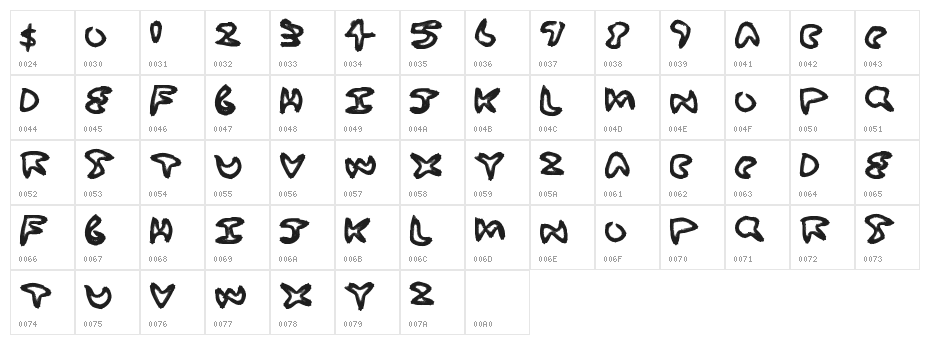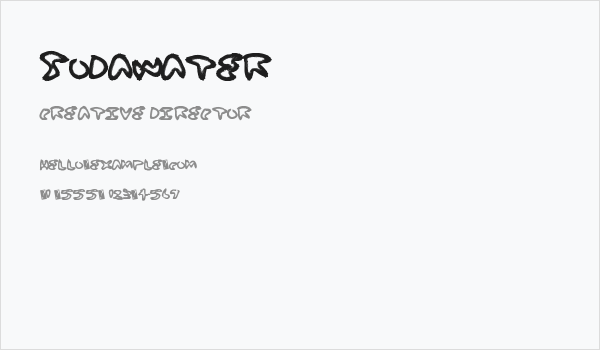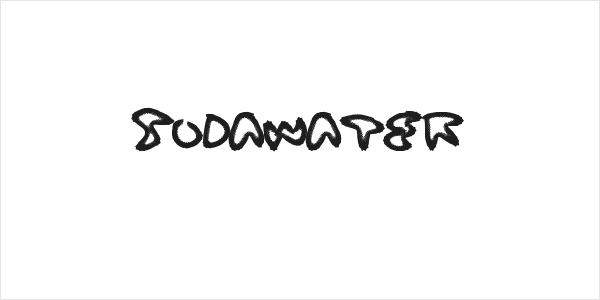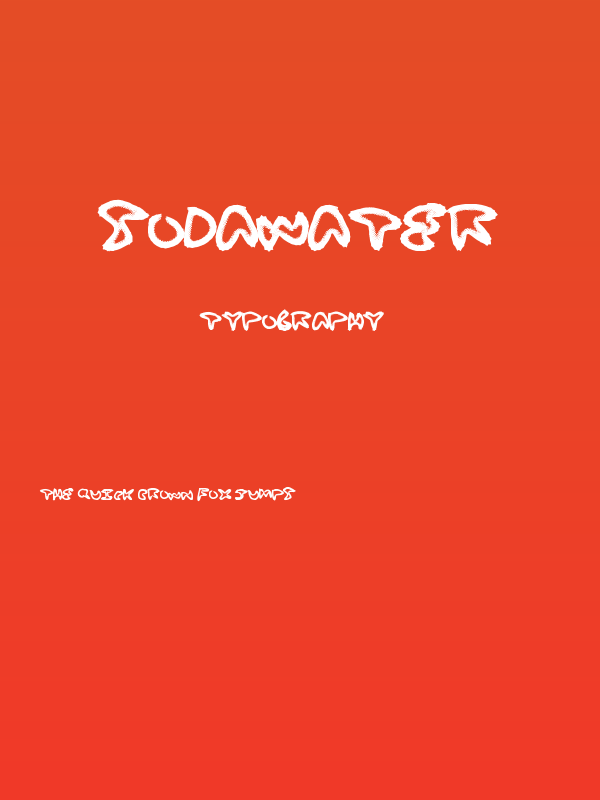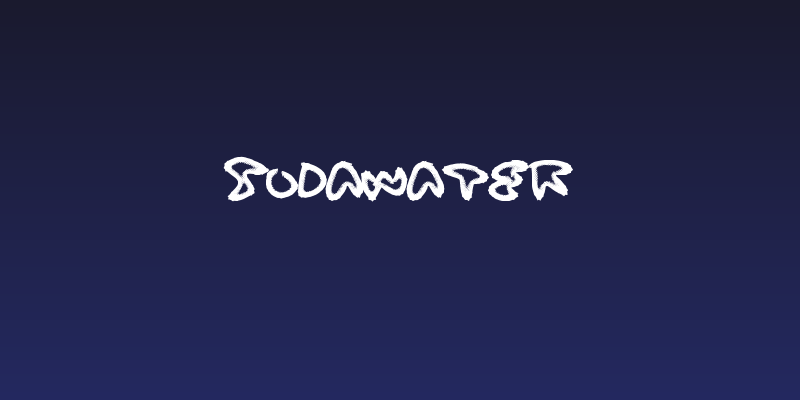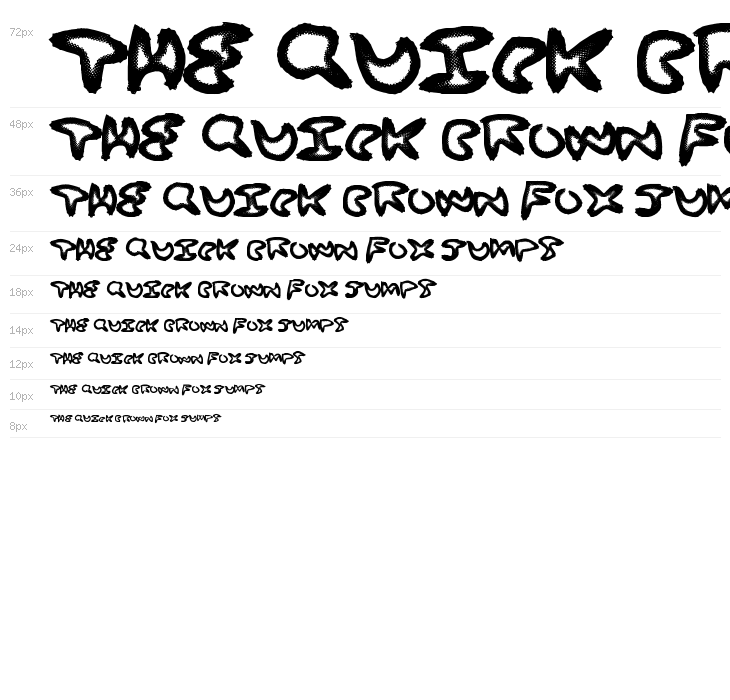
SodaWater Font
✎ Distorted Eroded
| Anwendungsfall | Logos, Posters, Creative Branding |
| Vorgeschlagene Projekte | Ideal for creative projects such as posters, logos, and branding materials that seek to convey energy and playfulness. |